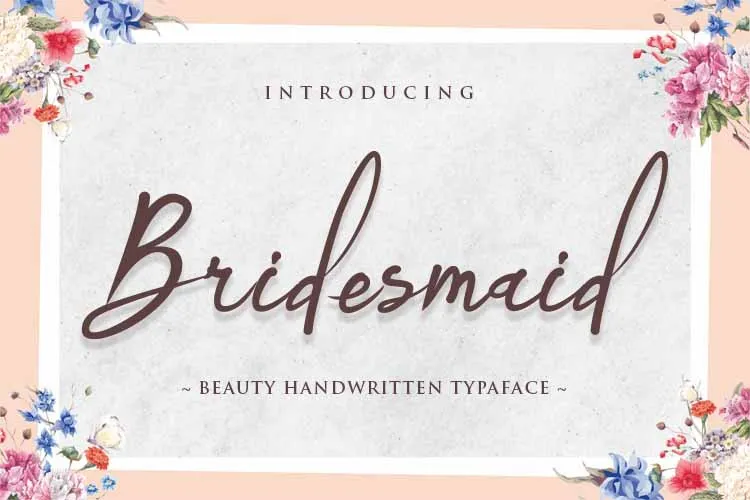
A Bridesmaid Font é uma deliciosa seleção de letras cursivas que traz um toque único e delicado para qualquer projeto de design. Ela se destaca como a escolha perfeita para encontros especiais como casamentos, onde você quer algo sofisticado e inovador, mas ainda com um sentimento autêntico e elegante. Suas características naturais e sua maneira única de ser escrita tornam essa fonte ideal tanto para cartões de agradecimento quanto para as mais belas citações ou frases personalizadas que desejas usar em suas lembranças de casamento. Além disso, ela é perfeita para qualquer tipo de design que necessite de uma pitada de mão-dura: seja um logo elaborado, cartões de negócios ou até mesmo a identidade visual de uma marca. A Bridesmaid Font não apenas complementará seu trabalho, mas também o destacará como criativo e único. Maknastd é o designer por trás dessa fonte elegante que se adapta perfeitamente para os mais diversos usos. Seja você um designer ou simplesmente alguém que gosta de fazer designs incríveis, essa fonte oferecerá um toque diferenciado a qualquer trabalho, tornando-o ainda mais memorável e personalizado.